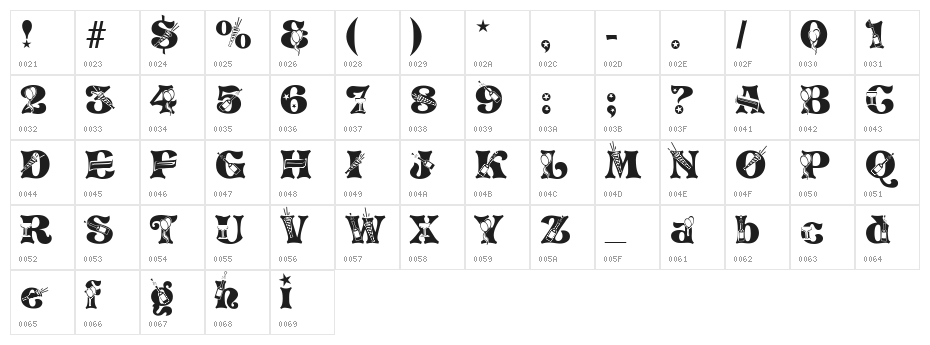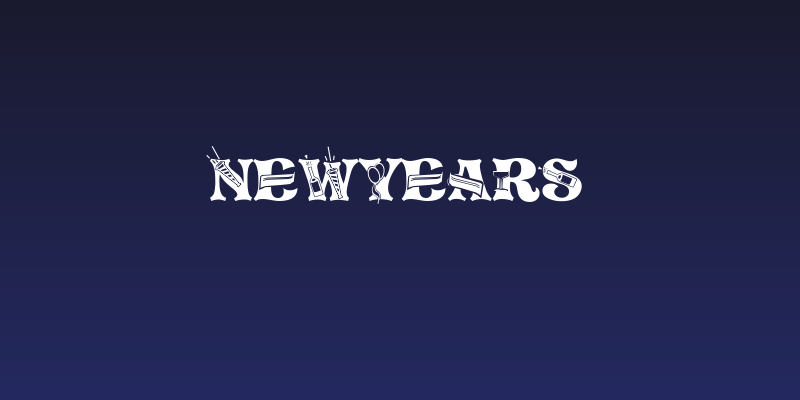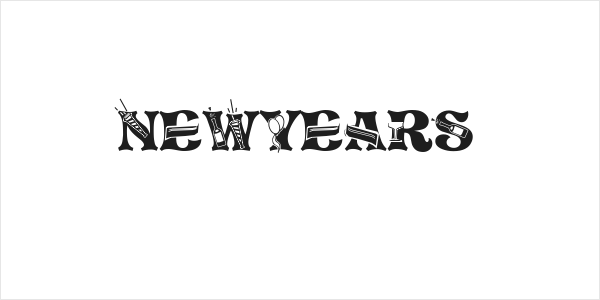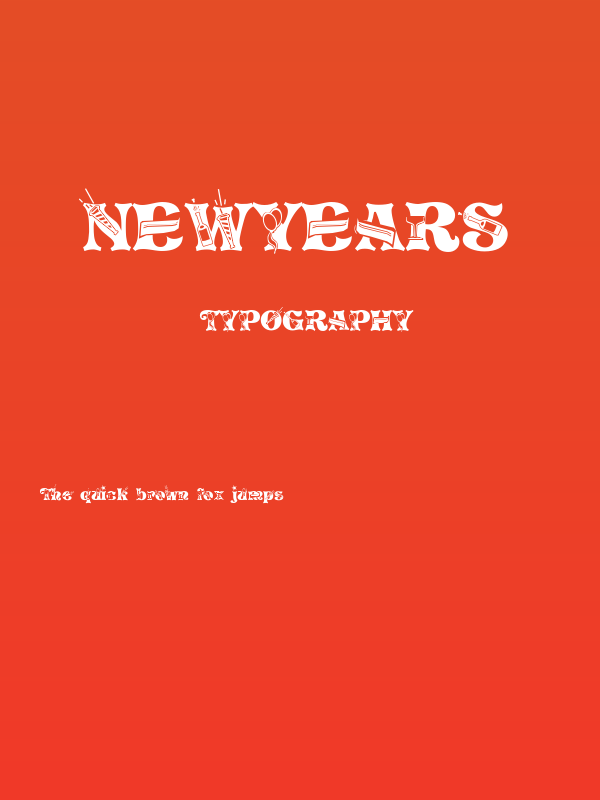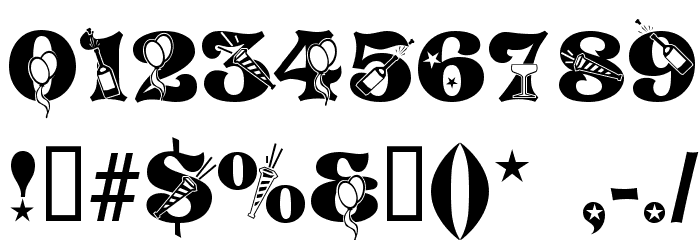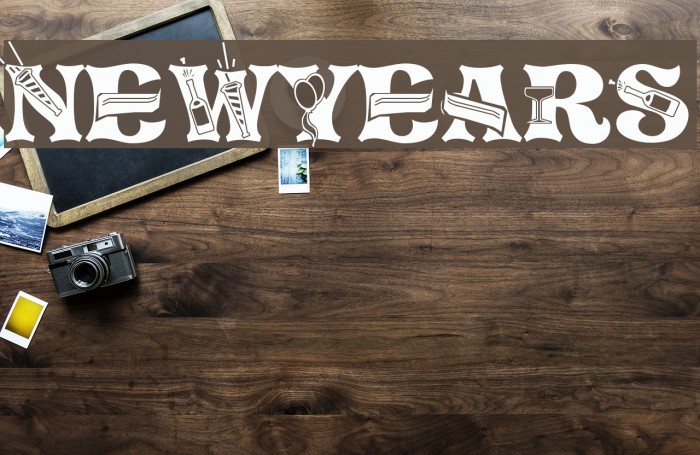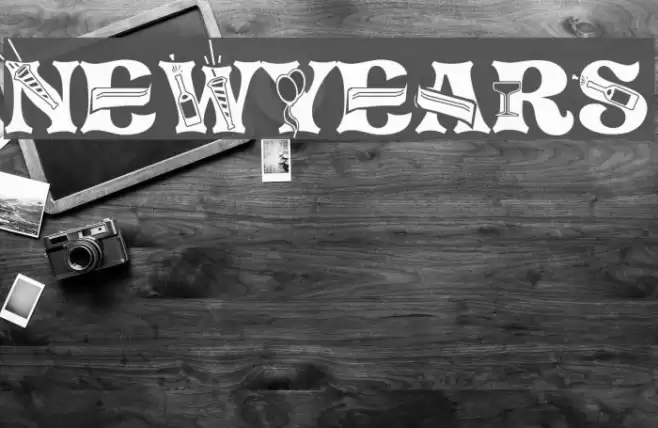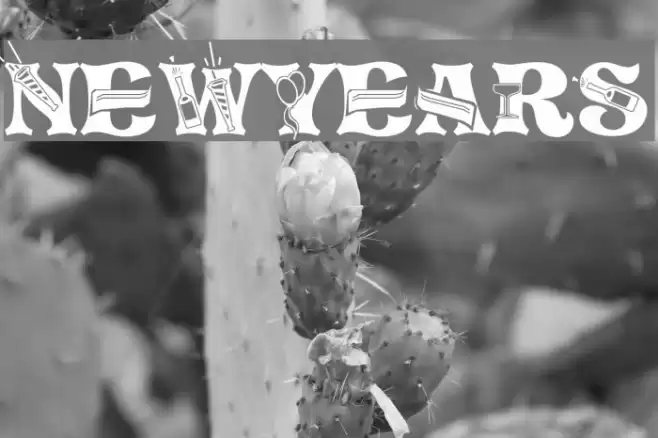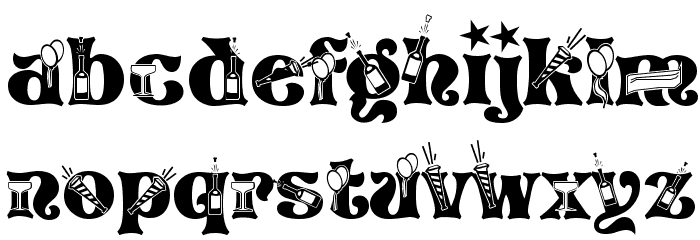
NEWYEARS Font
| Caz de utilizare | Headlines, Logos, Invitations |
| Proiecte propuse | Ideal for New Year's Eve invitations, party flyers, festive banners, and celebratory event branding. |